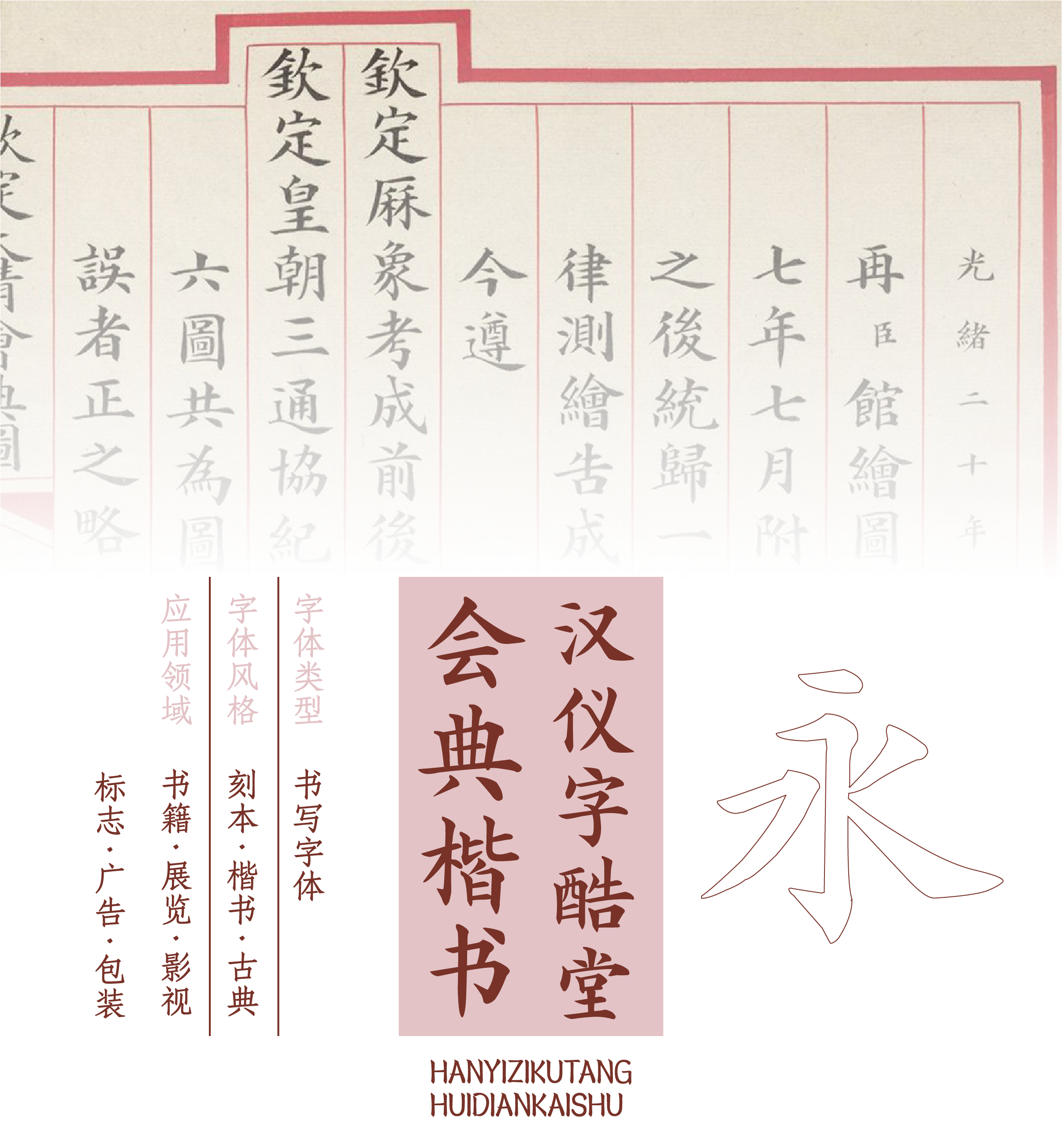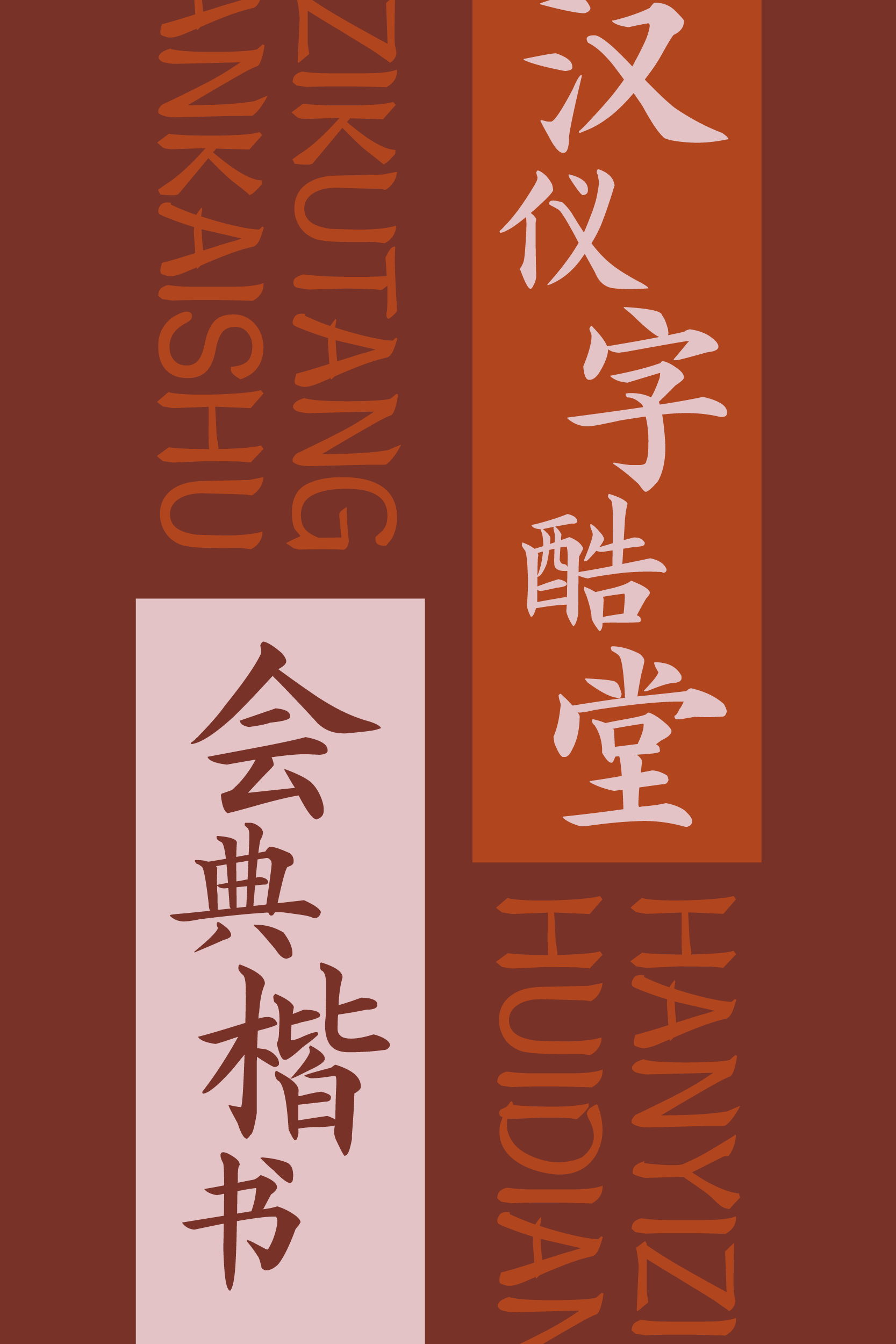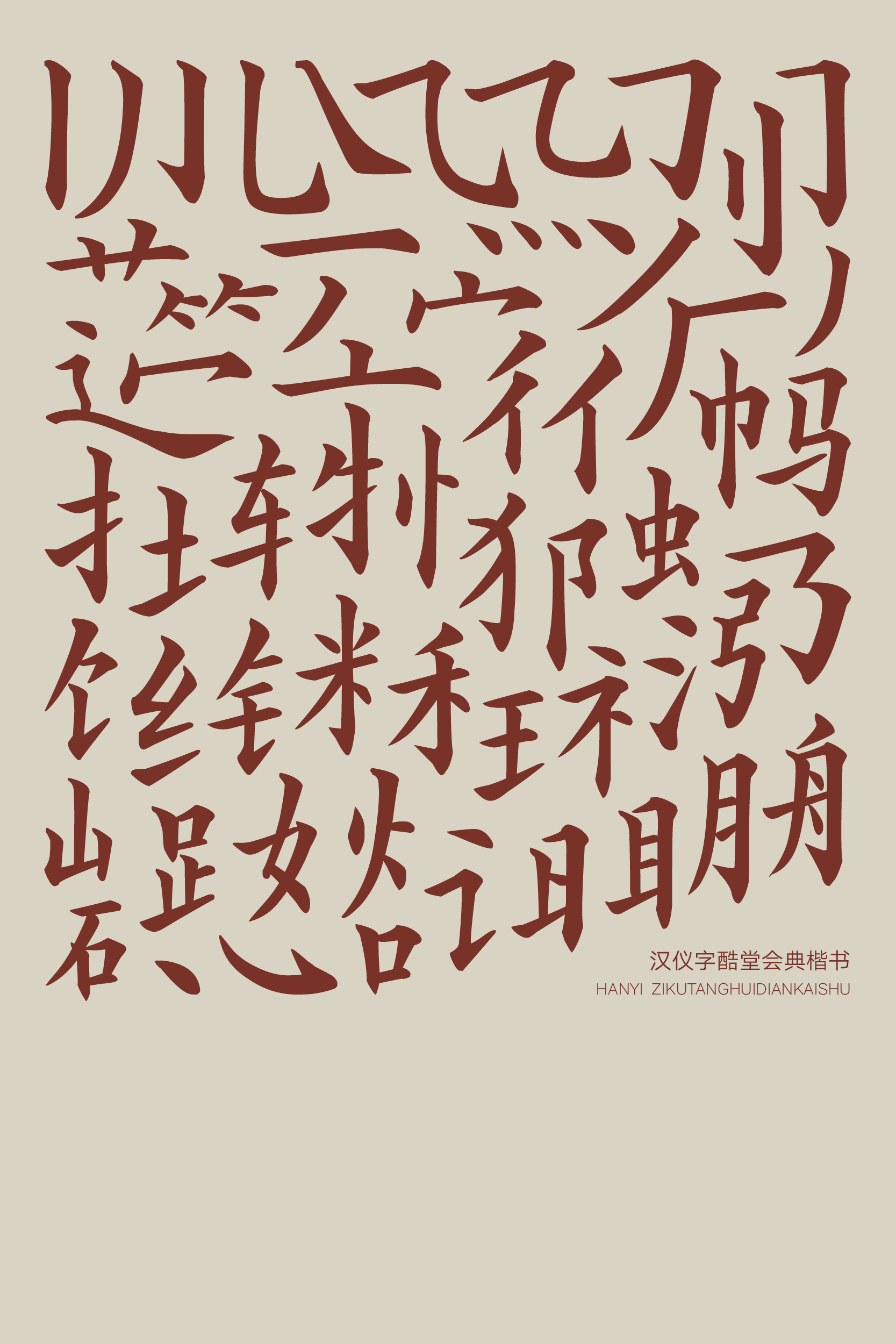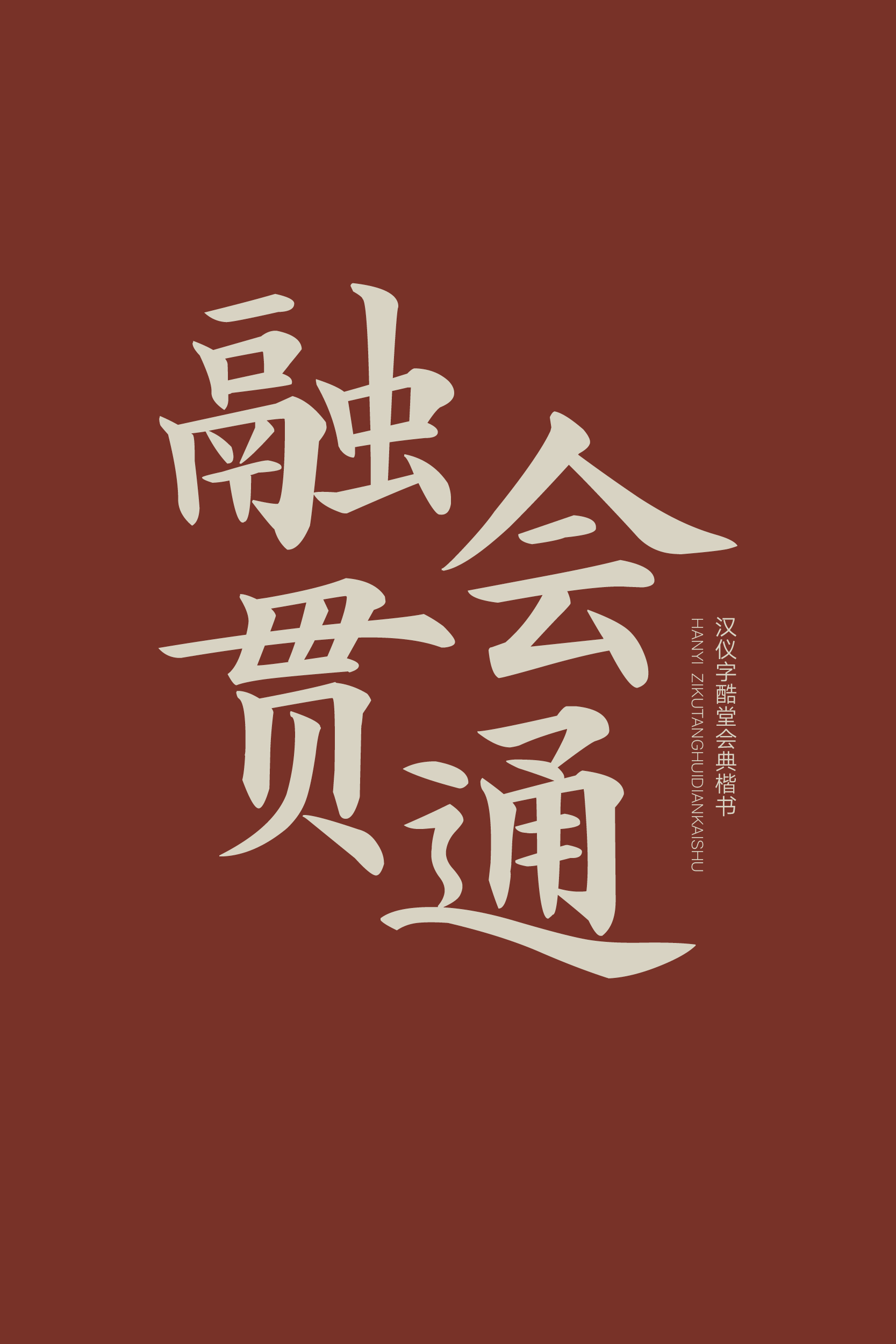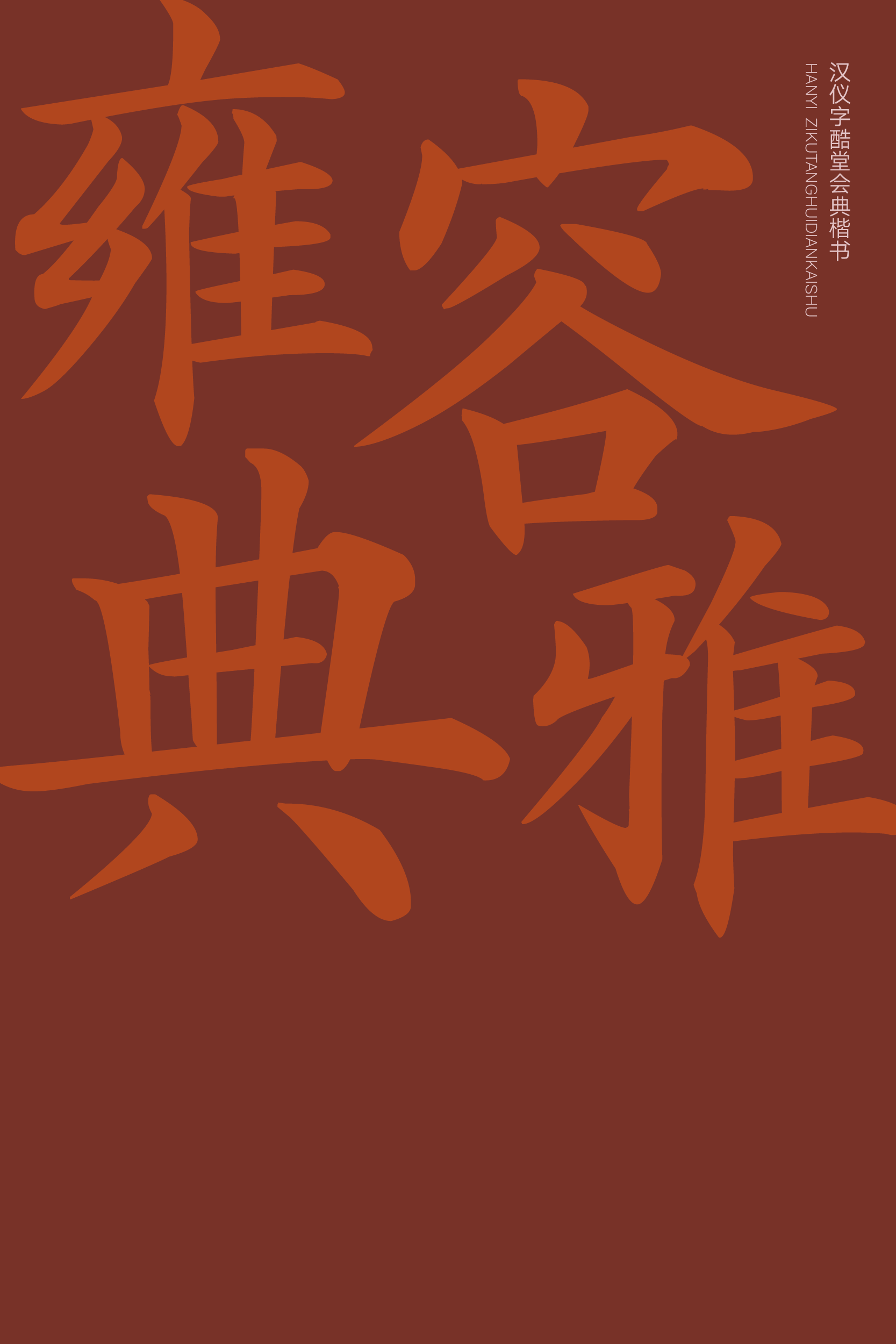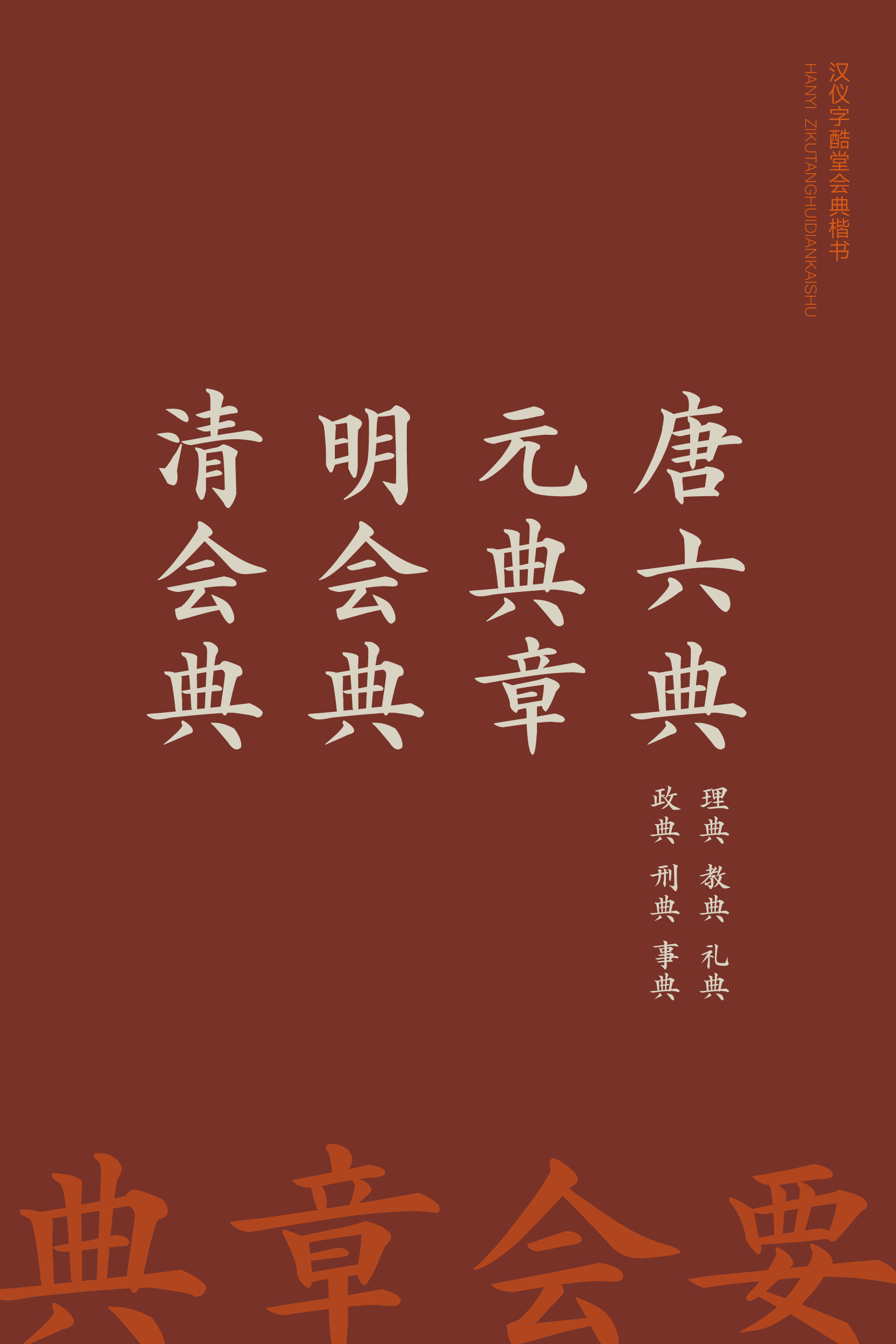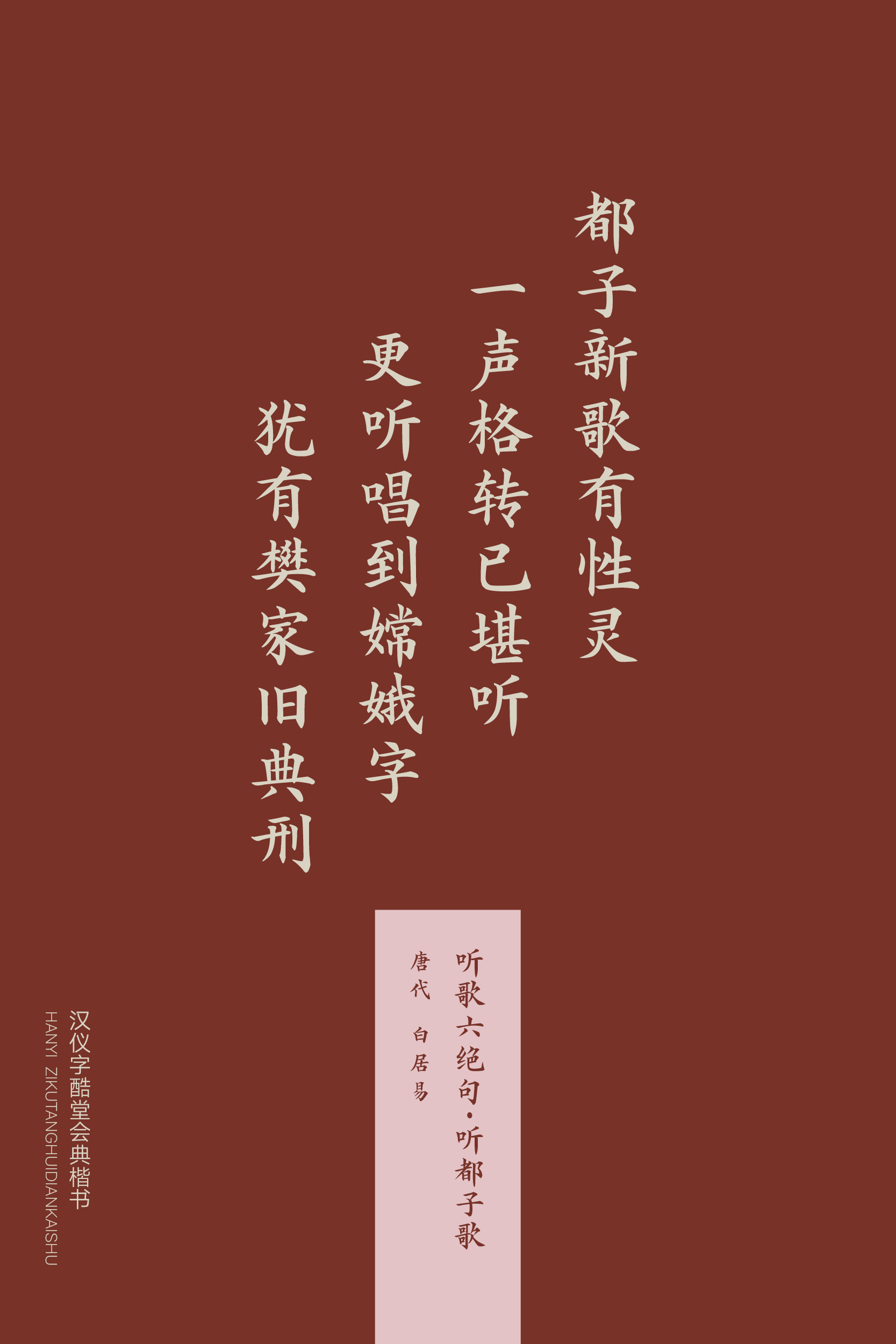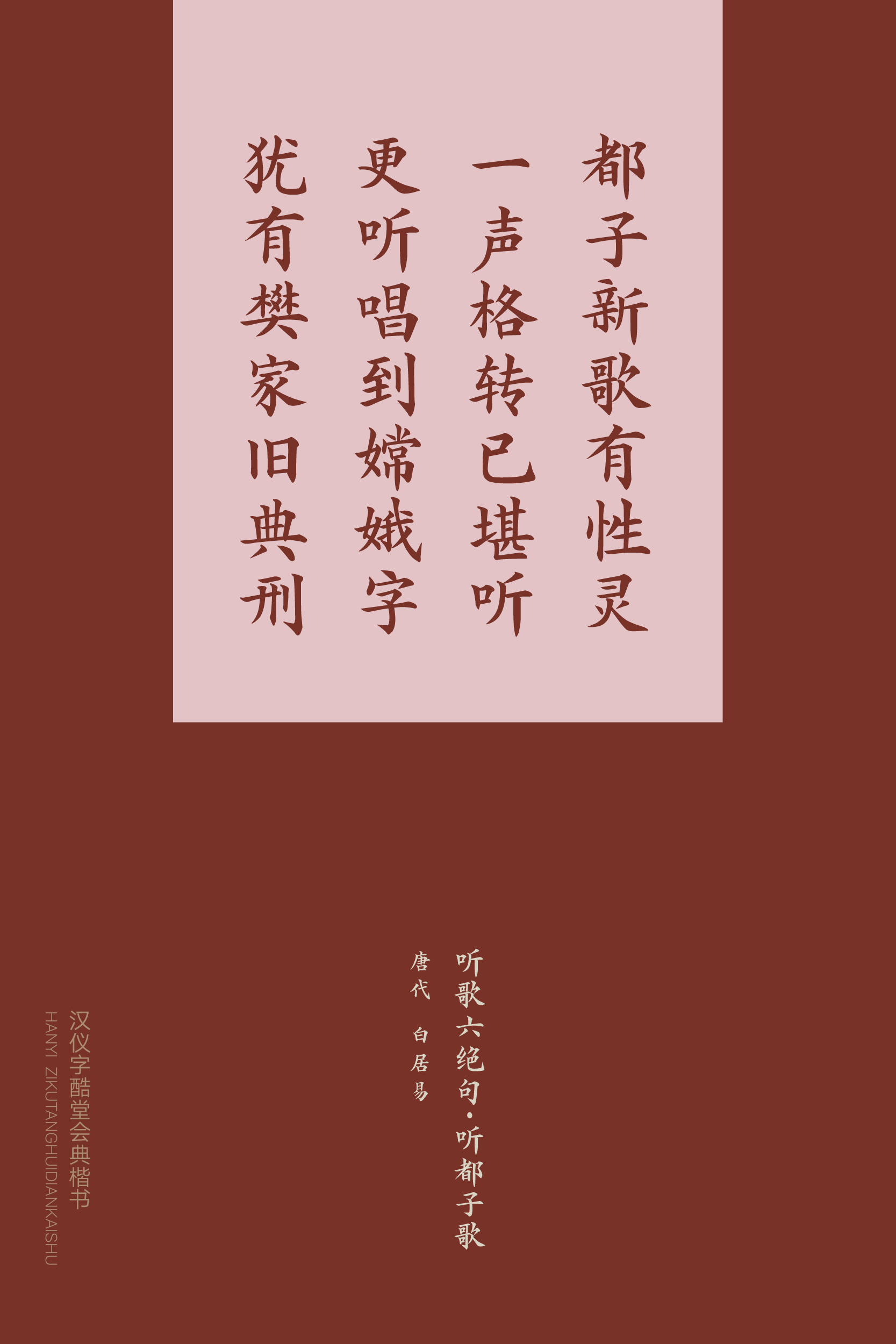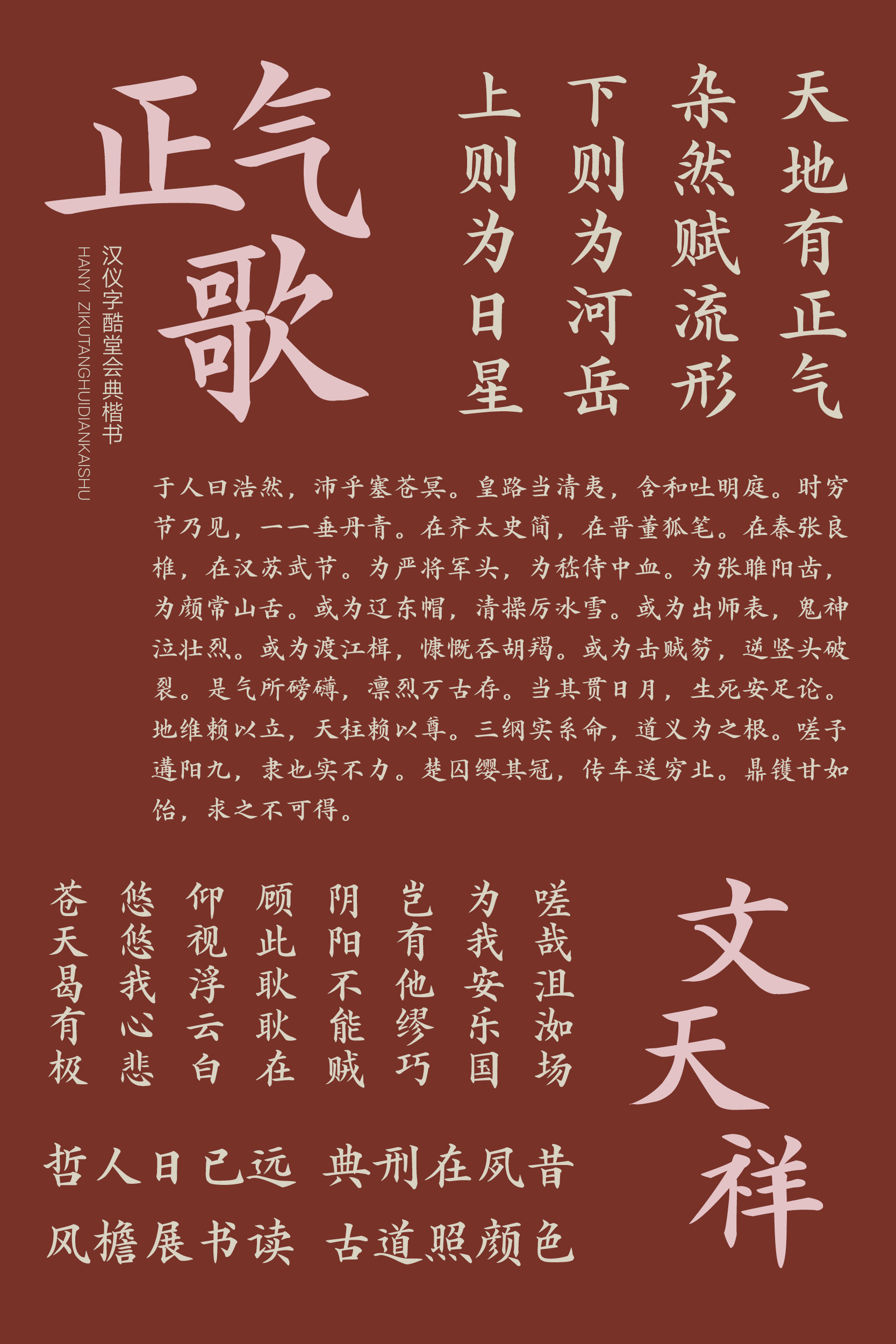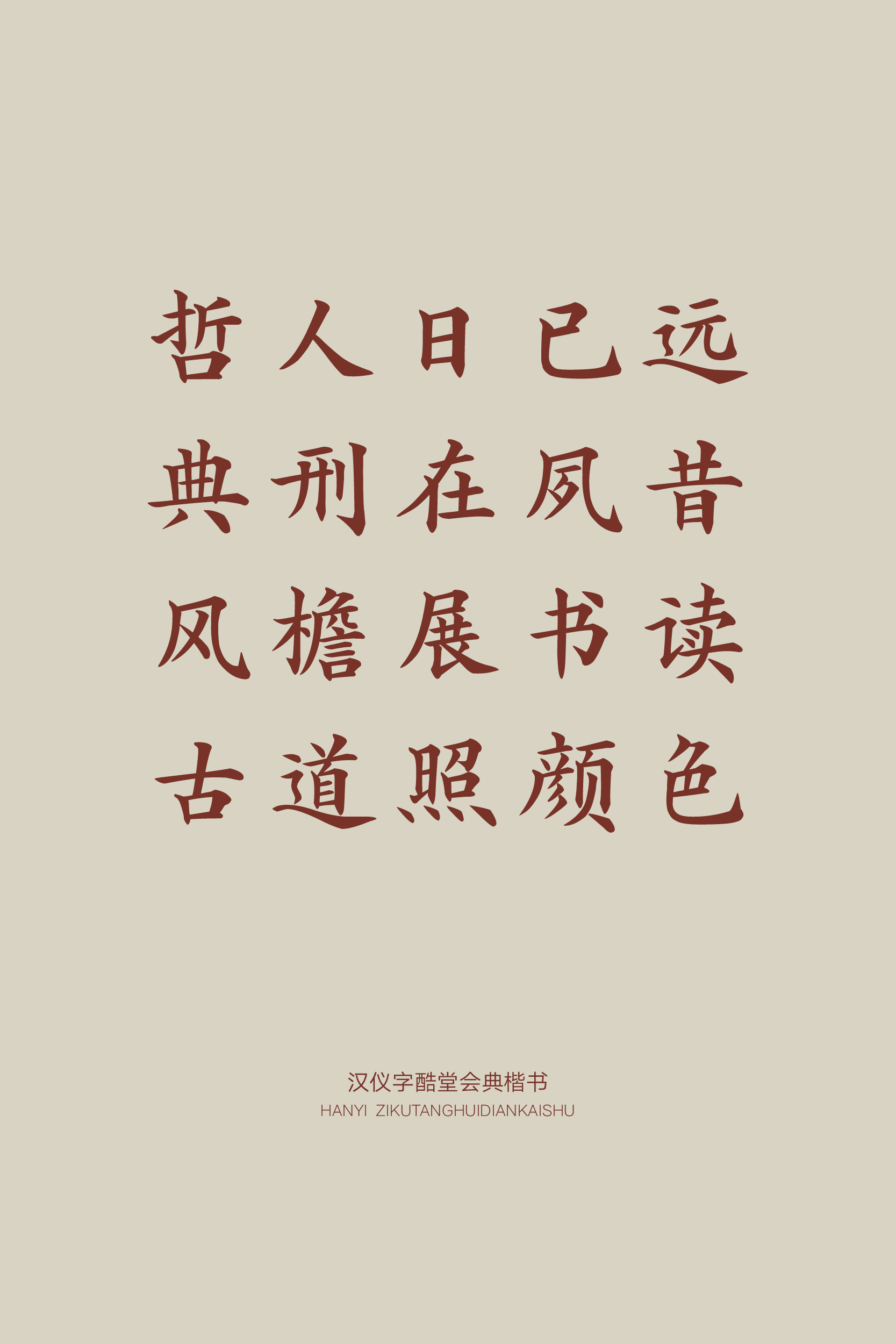
汉仪字酷堂会典楷书
汉仪字酷堂会典楷书,源于清光绪时期內府刊本《钦定大清会典图》,典则俊雅、清新秀逸,极大程度上保留了原刊本的风貌。字形端正,略为扁方,笔画有着浓重的写刻楷书韵味。这款复刻字体匀称而优美,适用于诗歌散文的排版、文化艺术类品牌设计、展览及出版物的视觉等多种使用场景。
汉仪字酷堂会典楷书极大程度上保留了原刊本的风貌:
字形端正,略为扁方。
强调右侧笔画,左轻右重。
写刻楷书韵味浓重。
部分笔画的书写沿用原刊本的笔形,添一分古意,多一丝变化。
西文造型更为窄长、紧凑,融合写刻楷书的笔意,中西文匹配端正而富于韵律。